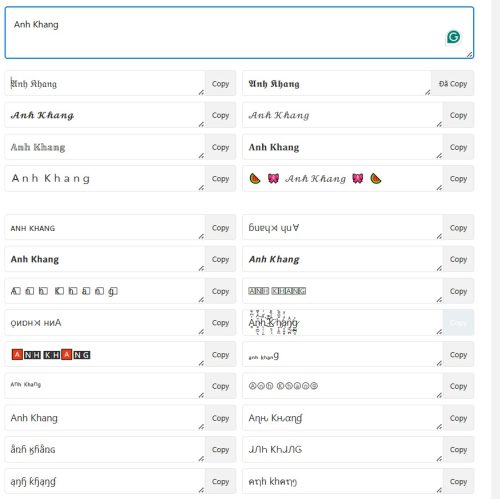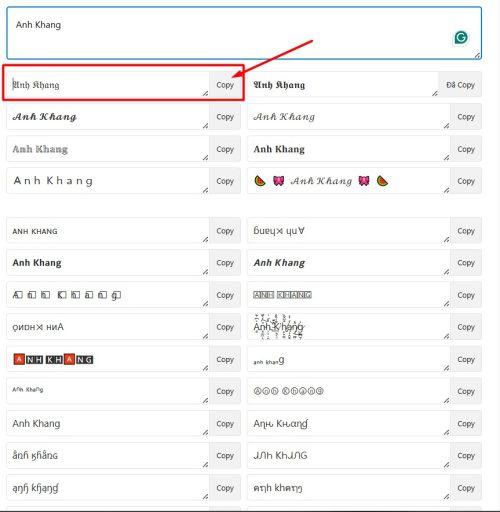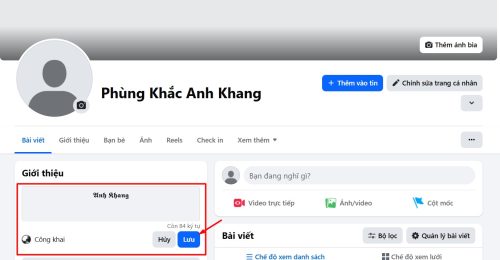
Font chữ đẹp ngày càng được sử dụng rộng rãi trong thiết kế, mạng xã hội, game hay đơn giản chỉ là soạn thảo nội dung nhờ khả năng tạo điểm nhấn và thể hiện phong cách rõ ràng. Trong bài viết này, bạn có thể khám phá các kiểu font chữ phổ biến, tải và cài đặt phông chữ trên máy rất nhanh chóng. Đặc biệt, bạn hoàn toàn có thể trải nghiệm công cụ tạo font chữ theo sở thích của mình hoàn toàn miễn phí được phát triển bởi 𝖋𝖔𝖓𝖙𝖈𝖍𝖚𝖆𝖓.𝖈𝖔𝖒, chỉ cần sao chép mà không cần cài đặt. Bộ công cụ này bạn có thể sử dụng ở bất kỳ đâu như: cập nhật trạng thái, tiểu sử, tin nhắn trên facebook, bình luận trên facebook, trên website, trên tiktok, trên twitter…
1. Hướng dẫn sử dụng công cụ tạo kiểu chữ đẹp thực tế
Để bạn dễ hình dung cách hoạt động của công cụ tạo kiểu chữ đẹp, hãy xem ví dụ thực tế dưới đây. Chỉ cần nhập văn bản bất kỳ, hệ thống sẽ tự động chuyển đổi sang nhiều kiểu chữ khác nhau để bạn sao chép và sử dụng ngay.
Bước 1: Nhập văn bản gốc của bạn.
Ví dụ: Anh Khang
Kết quả tạo kiểu chữ đẹp:
• 𝓐𝓷𝓱 𝓚𝓱𝓪𝓷𝓰
• 🅰🅽🅷 🅺🅷🅰🅽🅶
• 𝕬𝖓𝖍 𝕶𝖍𝖆𝖓𝖌
Bước 2: Chọn kiểu chữ bạn mong muốn trong danh sách bản xem trước và lựa chọn Copy văn bản đã chuyển đổi
Bước 3: Dán vào Bio Social bạn mong muốn và nhấn Lưu để hoàn thành.
Sau khi đã chọn được kiểu chữ ưng ý, bạn hoàn toàn có thể áp dụng ngay vào phần bio trên các nền tảng phổ biến như Facebook, Instagram hay TikTok. Riêng với Facebook, mỗi kiểu chữ sẽ hiển thị và tương thích khác nhau, vì vậy bạn có thể tham khảo chi tiết thêm hướng dẫn dưới đây sẽ giúp bạn tối ưu phần giới thiệu cá nhân sao cho nổi bật mà vẫn dễ đọc.
2.1. Font chữ có sẵn đa dạng
• Font chữ cơ bản: Serif và Sans-serif hiện đại, gọn gàng và phù hợp với giao diện số
• Font chữ nổi bật: Display Fonts, chữ vuông, chữ bong bóng có hình khối rõ ràng, dễ gây ấn tượng.
• Font chữ viết tay: Handwriting và Brush Script tự nhiên hoặc vẽ bằng cọ, mang lại cảm giác mềm mại.
• Font trang trí, ký tự đặc biệt: Ký tự đặc biệt, chữ viền, chữ lộn ngược, chữ nhỏ trên và các dạng ký tự biến thể khác.
• Font chữ cổ điển: Kiểu chữ Gothic, Fraktur, Vintage / Retro tạo cảm giác hoài niệm và huyền bí.
• Font kỹ thuật: Monospace là nhóm font có độ rộng ký tự đồng đều, mang cảm giác công nghệ, máy móc và chính xác.
2.2. Tính năng tạo phông chữ đẹp thông minh
• Giao diện thân thiện: Thiết kế font chữ đặc biệt tối giản, trực quan, hỗ trợ thao tác nhanh chóng trên cả máy tính và điện thoại.
• Bộ sưu tập gần 100 mẫu chữ: Chữ in đậm, chữ nghiêng, chữ cách điệu, chữ kèm kí tự đặc biệt đẹp, font chữ gothic, chữ lộn ngược, chữ cách điệu, kiểu chữ đặc biệt, đổi phông chữ.…
• Văn bản thuần Unicode: Đảm bảo tương thích tuyệt đối khi sao chép và chia sẻ, giúp bạn đăng tải thông điệp mà không lo gặp lỗi hiển thị.